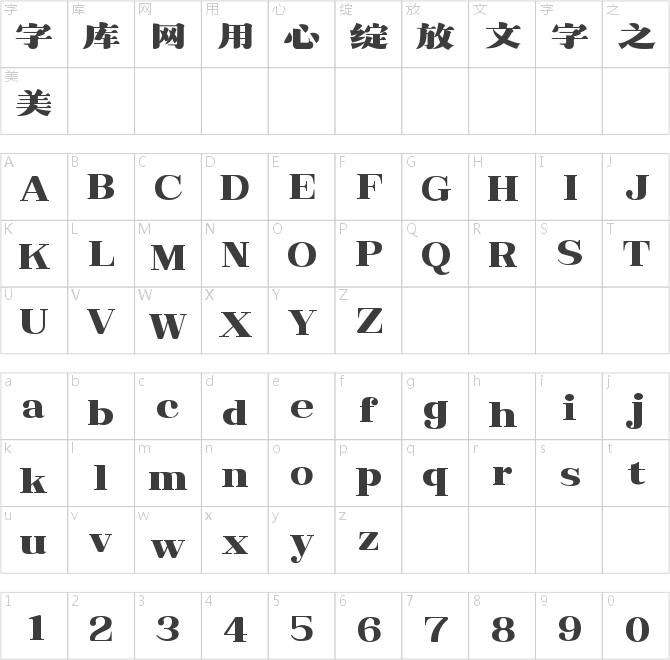
字體名稱: 爾雅福祿宋
爾雅福祿宋
爾雅福祿宋字體字庫(kù)是一款讓人賞心悅目、百看不厭的中文字體,適合各類廣告和產(chǎn)品包裝設(shè)計(jì)應(yīng)用,字體大小2.86MB,格式為ttf字體,上傳用戶是志誠(chéng)設(shè)計(jì),作者/版權(quán)方為爾雅字庫(kù)